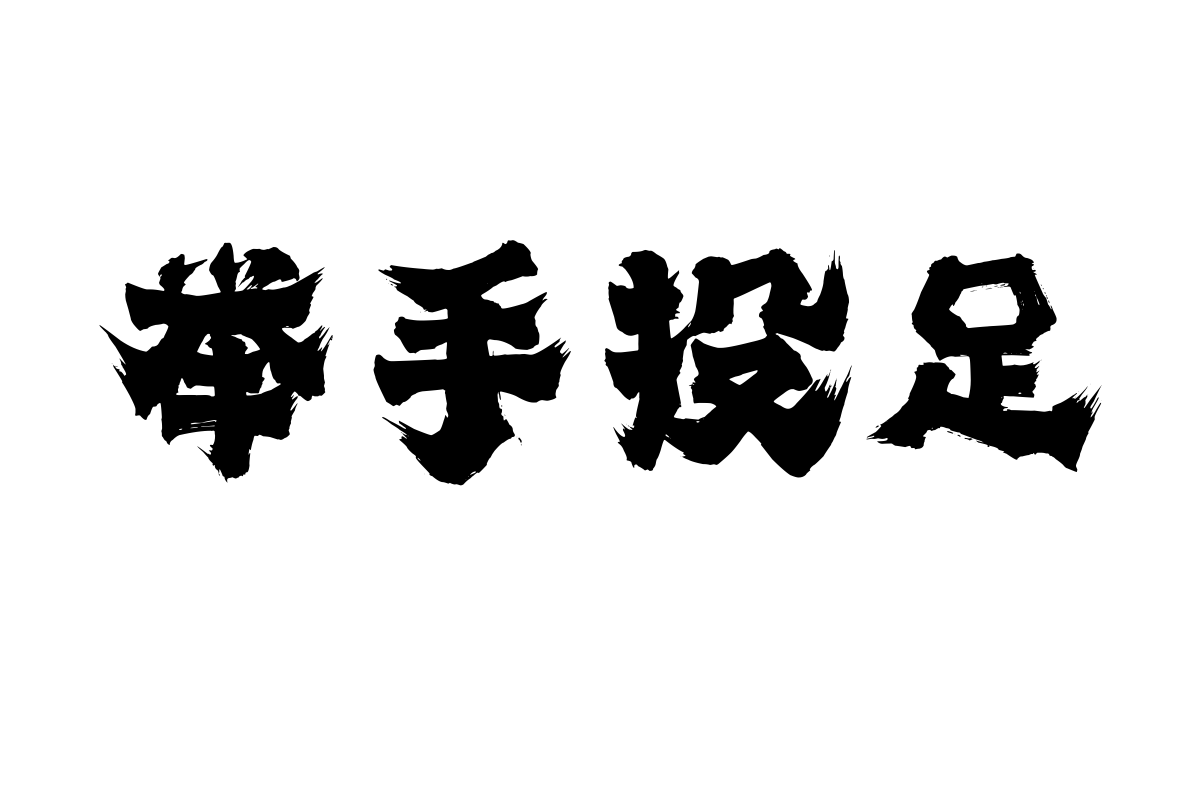
上首狂霸手写体是一款具有独特风格的中文字体,它的特点是笔画粗犷、结构紧凑,给人一种豪放不羁的感觉。这款字体适用于需要强调个性和力量的场合,如广告设计、产品包装、宣传海报等。
上首狂霸手写体的字形特点如下:
1. 笔画粗细适中,既有力度又有柔美,能够很好地传达出作者的情感和态度。
2. 结构紧凑,线条流畅,给人一种简洁而有力的视觉效果。
3. 字形大小不一,既有大字也有小字,可以根据需要进行选择和搭配。
4. 适用于多种场景,无论是在正式的商业环境中还是在轻松的个人使用中,都能够展现出独特的魅力。